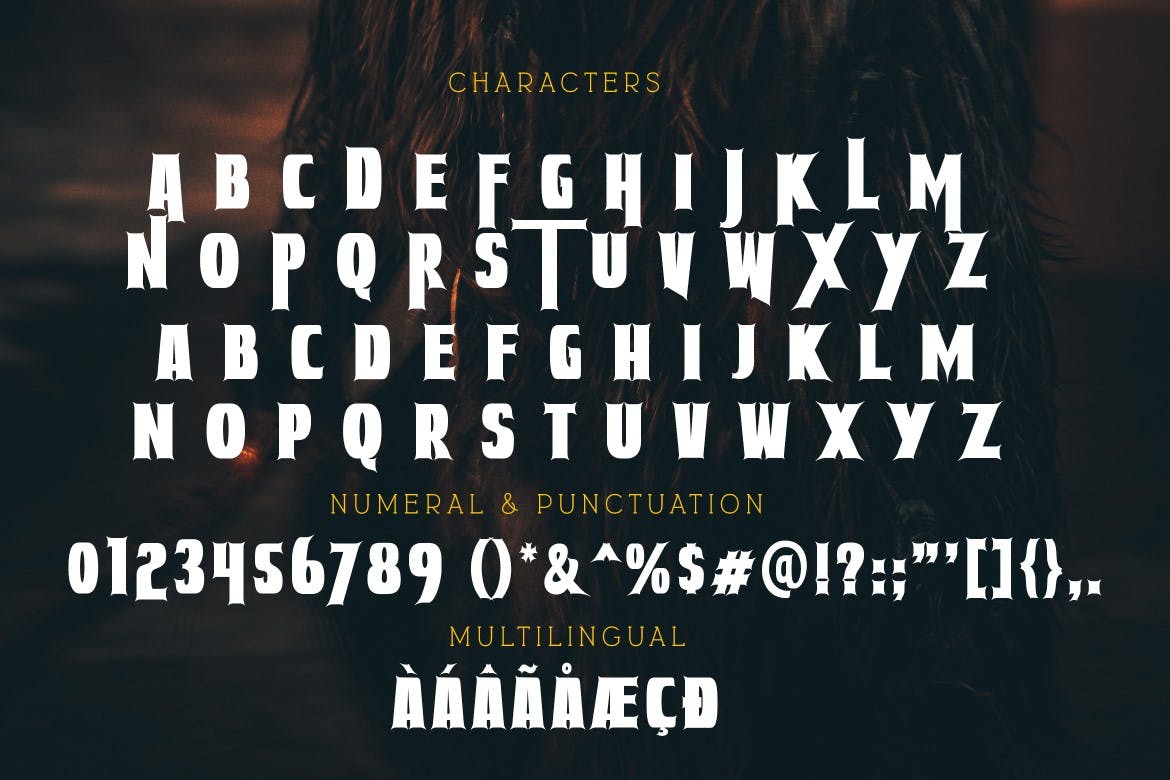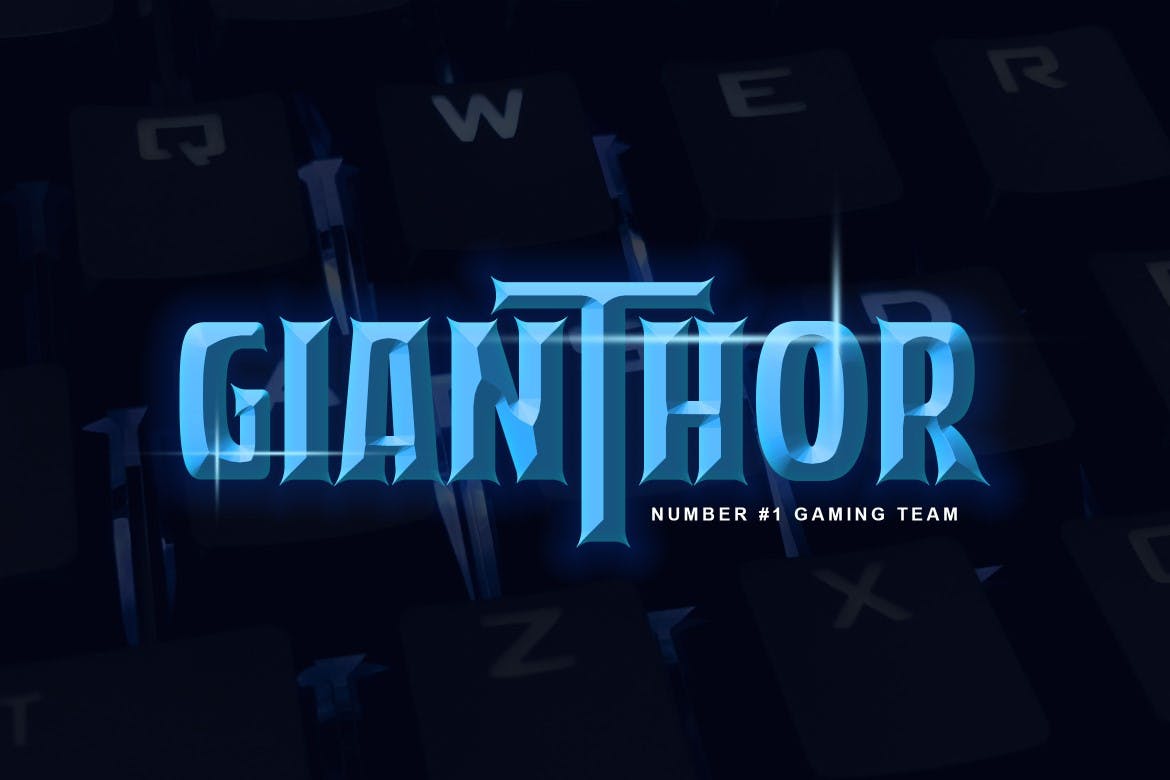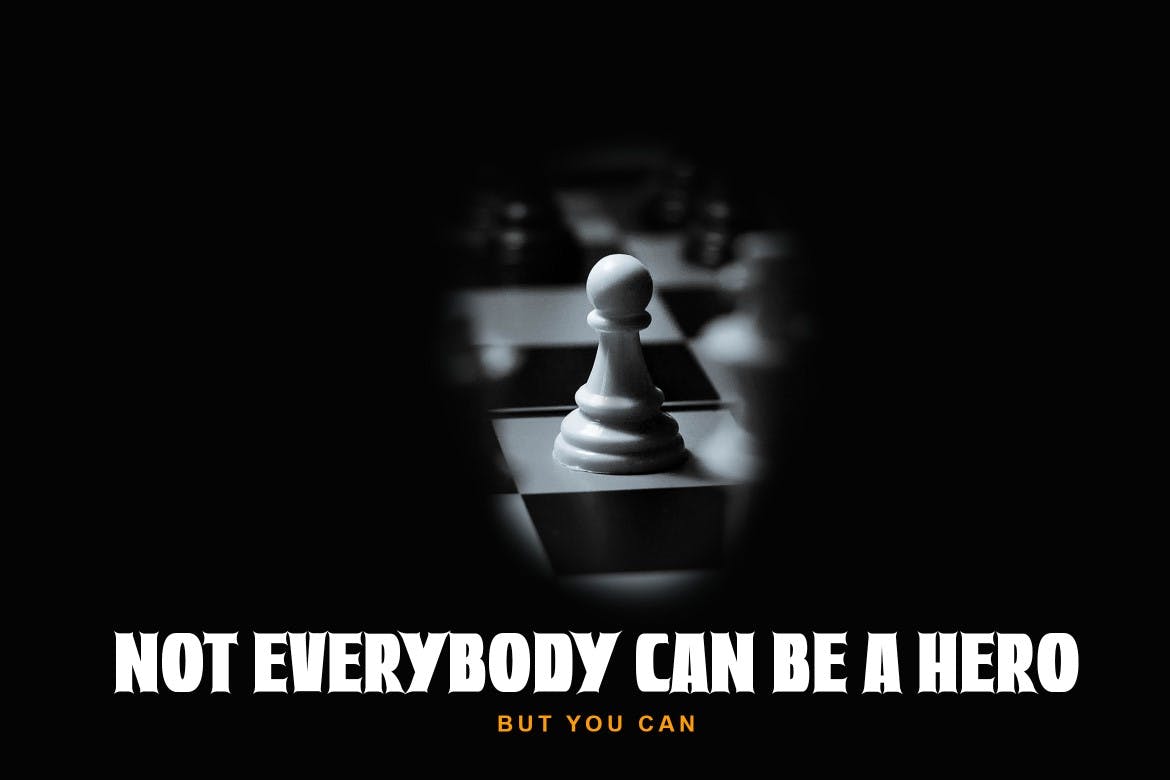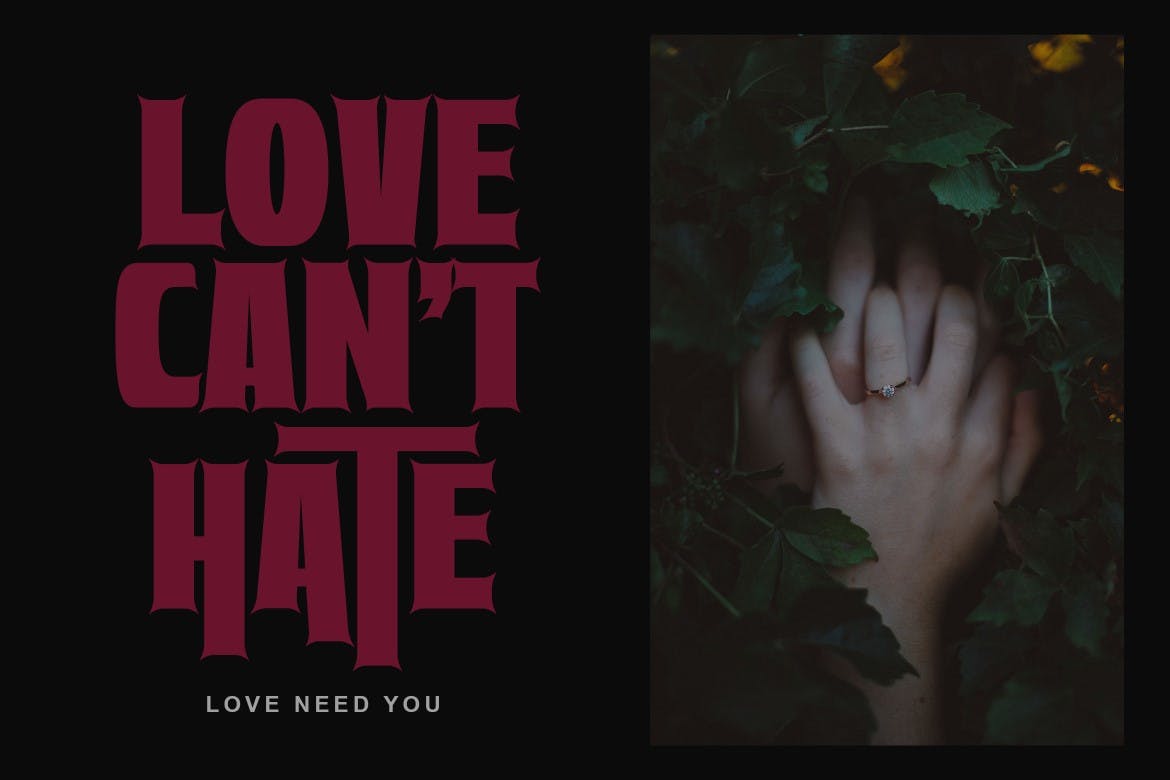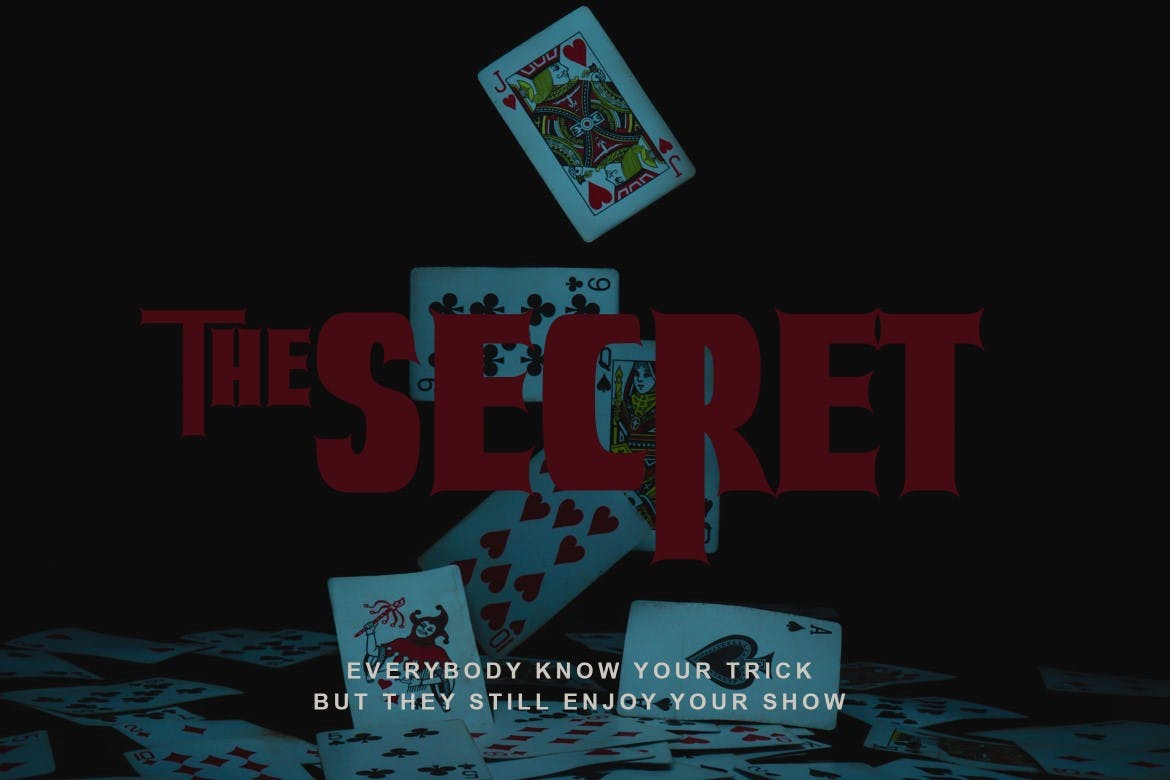
Devil Hunter Esport Logo Font
فونت Devil Hunter، انتخابی بی‌نظیر برای طراحی لوگوهای ای‌اسپورت.
فونت Devil Hunter یک فونت لوگوی ای‌اسپورت خلاقانه و جذاب است. این فونت به راحتی با مجموعه‌ای بزرگ از پروژه‌ها هماهنگ می‌شود، بنابراین آن را به ایده‌های خلاقانه خود اضافه کنید و ببینید چگونه باعث برجسته شدن آن‌ها می‌شود! از این فونت برای طراحی لوگوهای ای‌اسپورت خود استفاده کنید.
• مناسب برای طراحی لوگوهای ای‌اسپورت
• قابل استفاده در پروژه‌های گرافیکی مختلف
• ایجاد جلوه‌ای خاص و منحصر به فرد در طراحی‌های شما